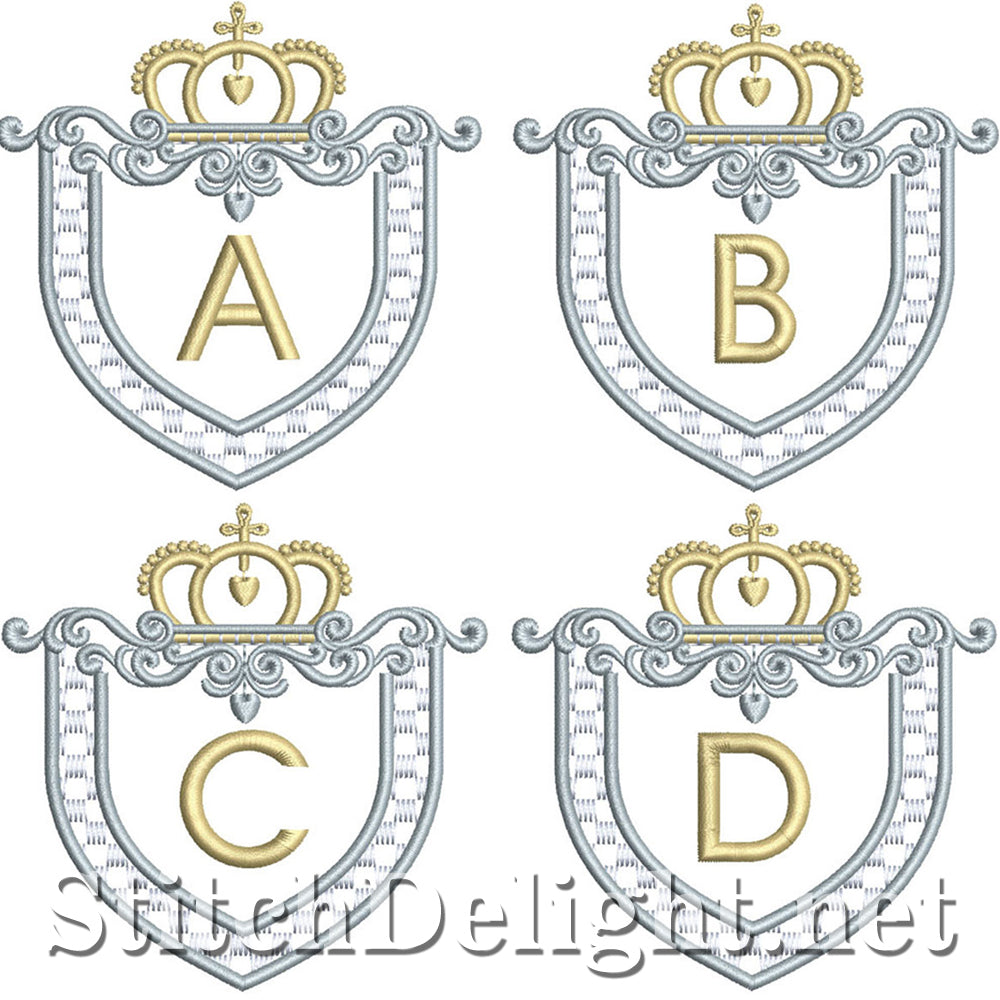
Belle police digne de la royauté, cette police est superbe sur le lin - elle comprend un cadre vierge pour que vous puissiez ajouter votre propre motif ou lettrage au centre - La taille du cadre est de 3,71 x 3,89 ", compte environ 7 900 points - Les lettres que j'ai utilisées le nouveau type de remplissage de point appelé Satin surélevé, qui imite la broderie en mousse, donc elle est plus soulevée du tissu que les autres points, pas de mousse nécessaire